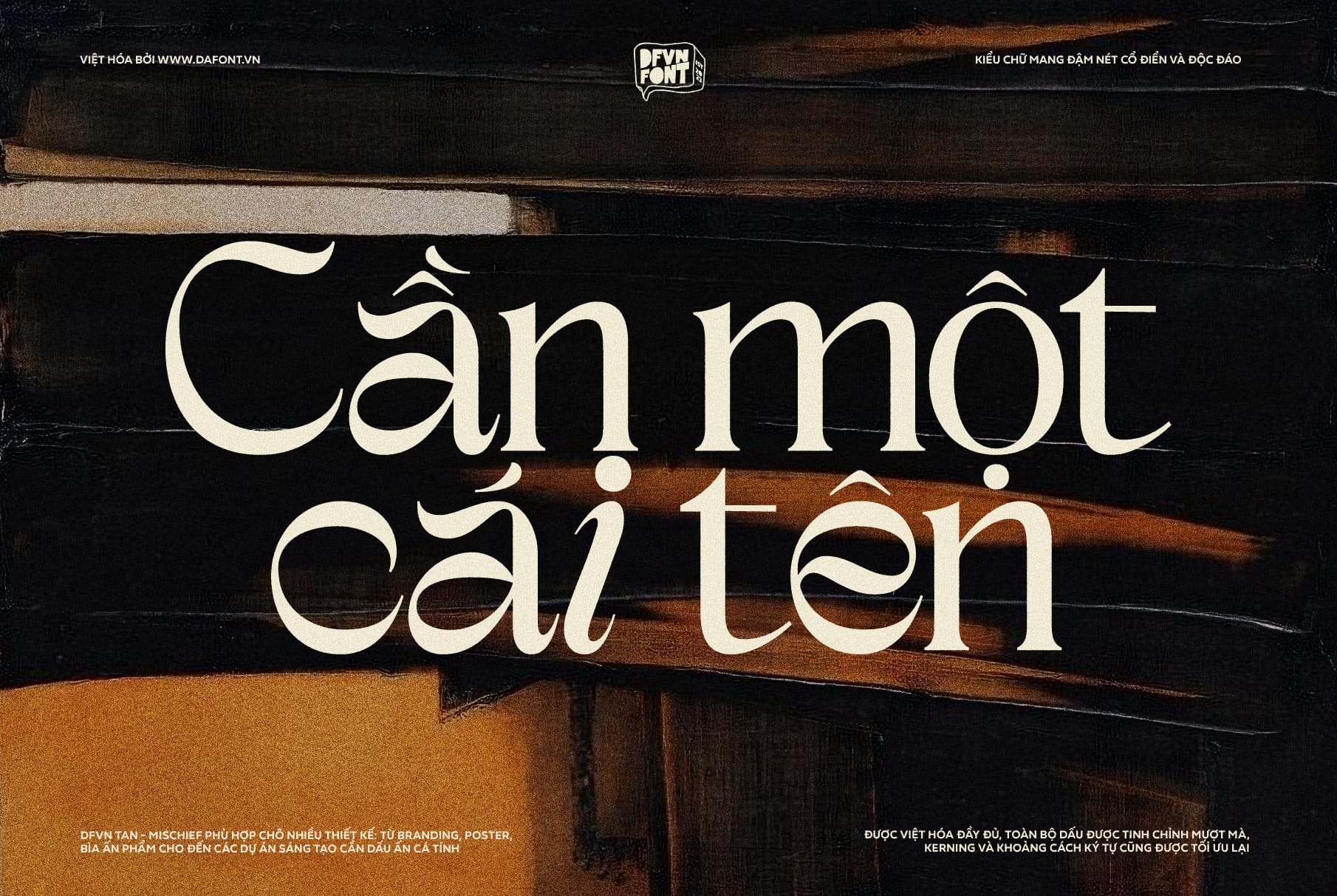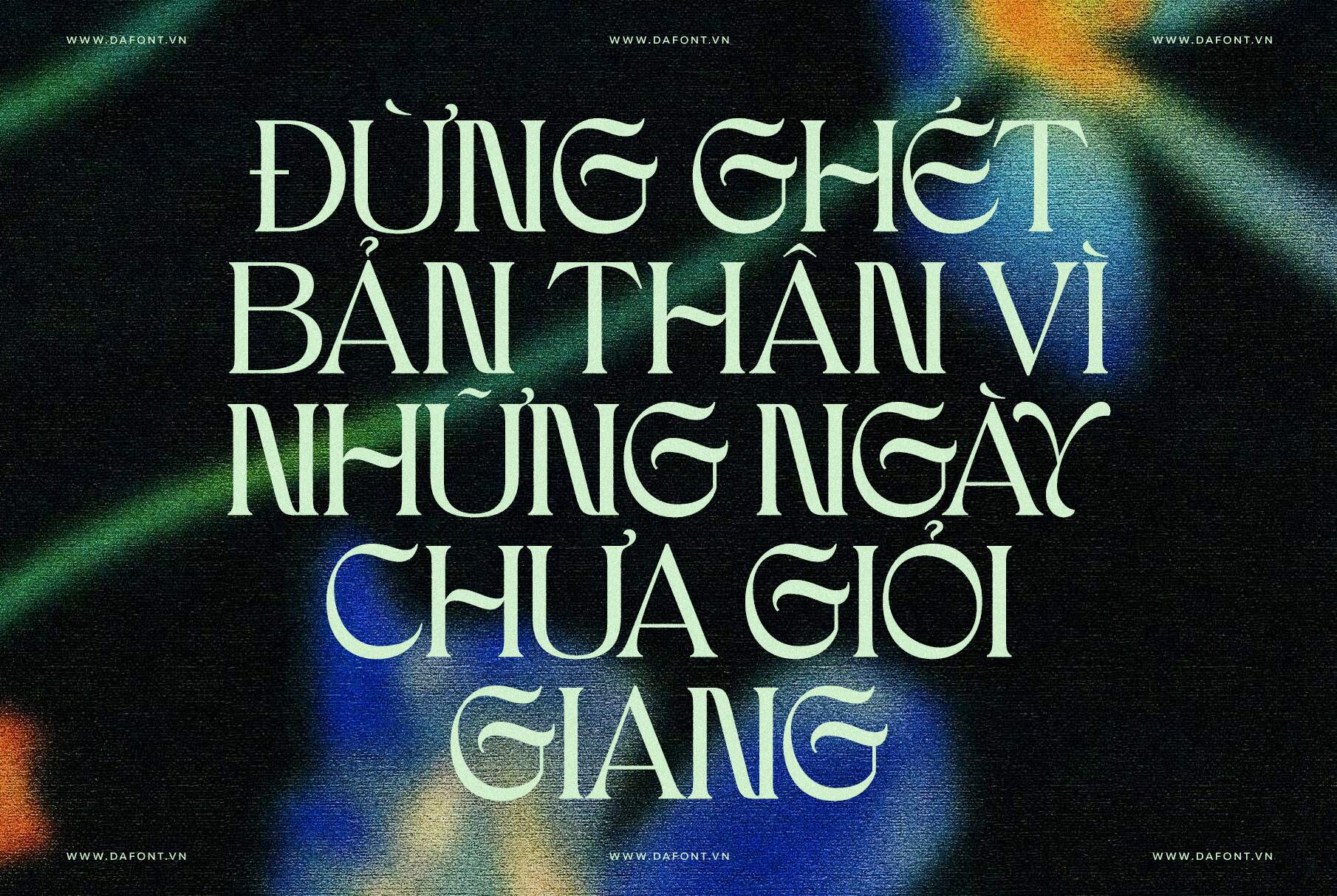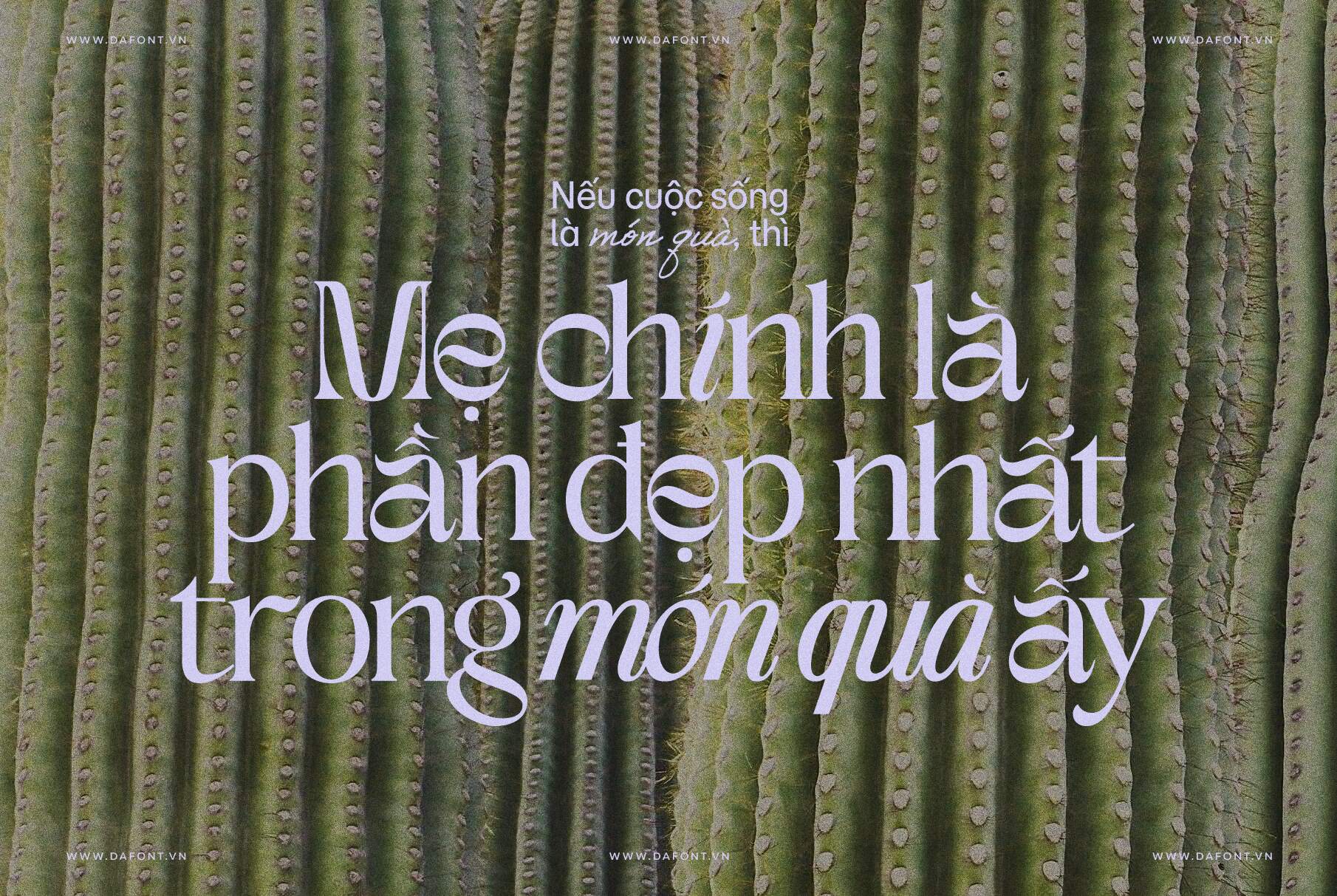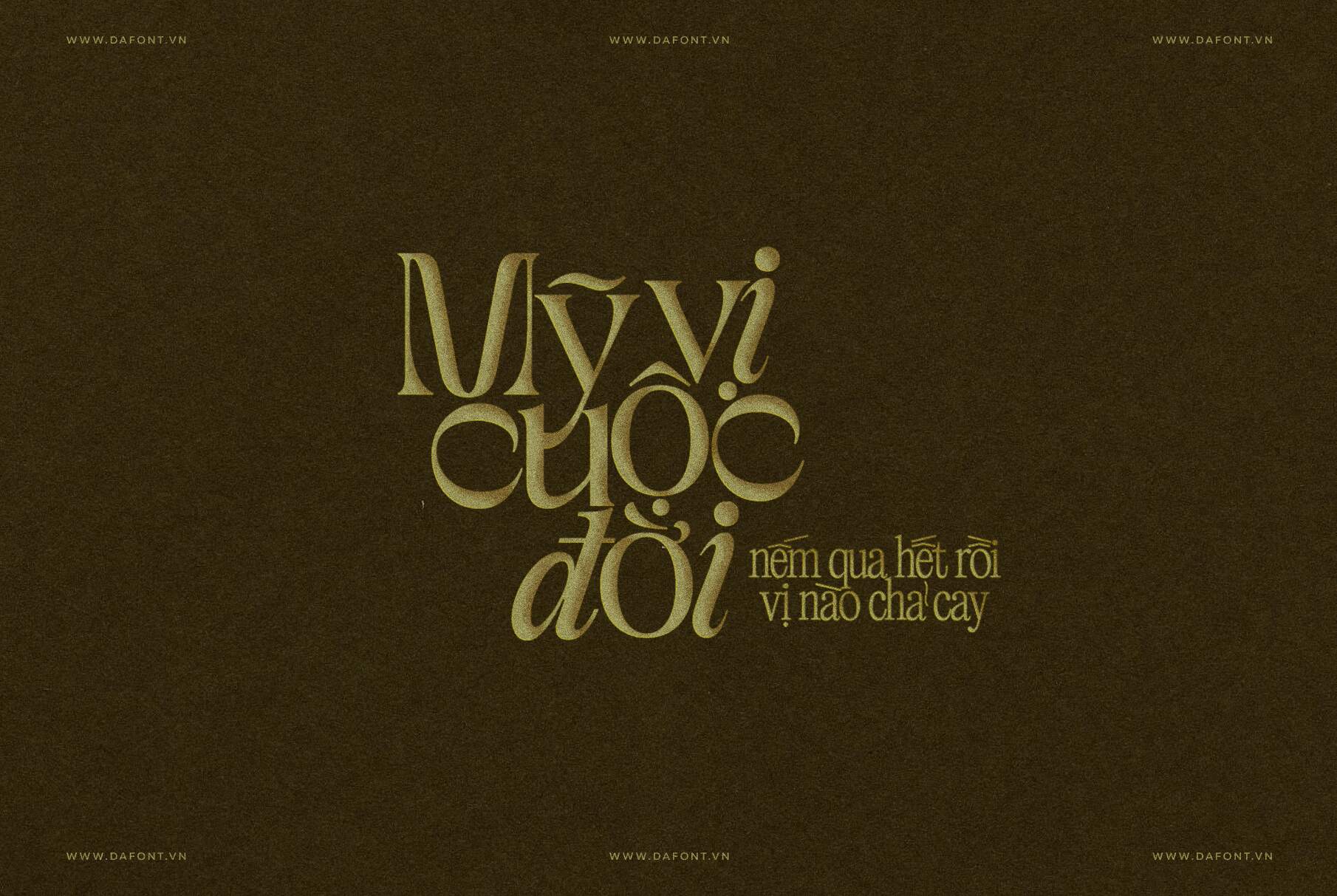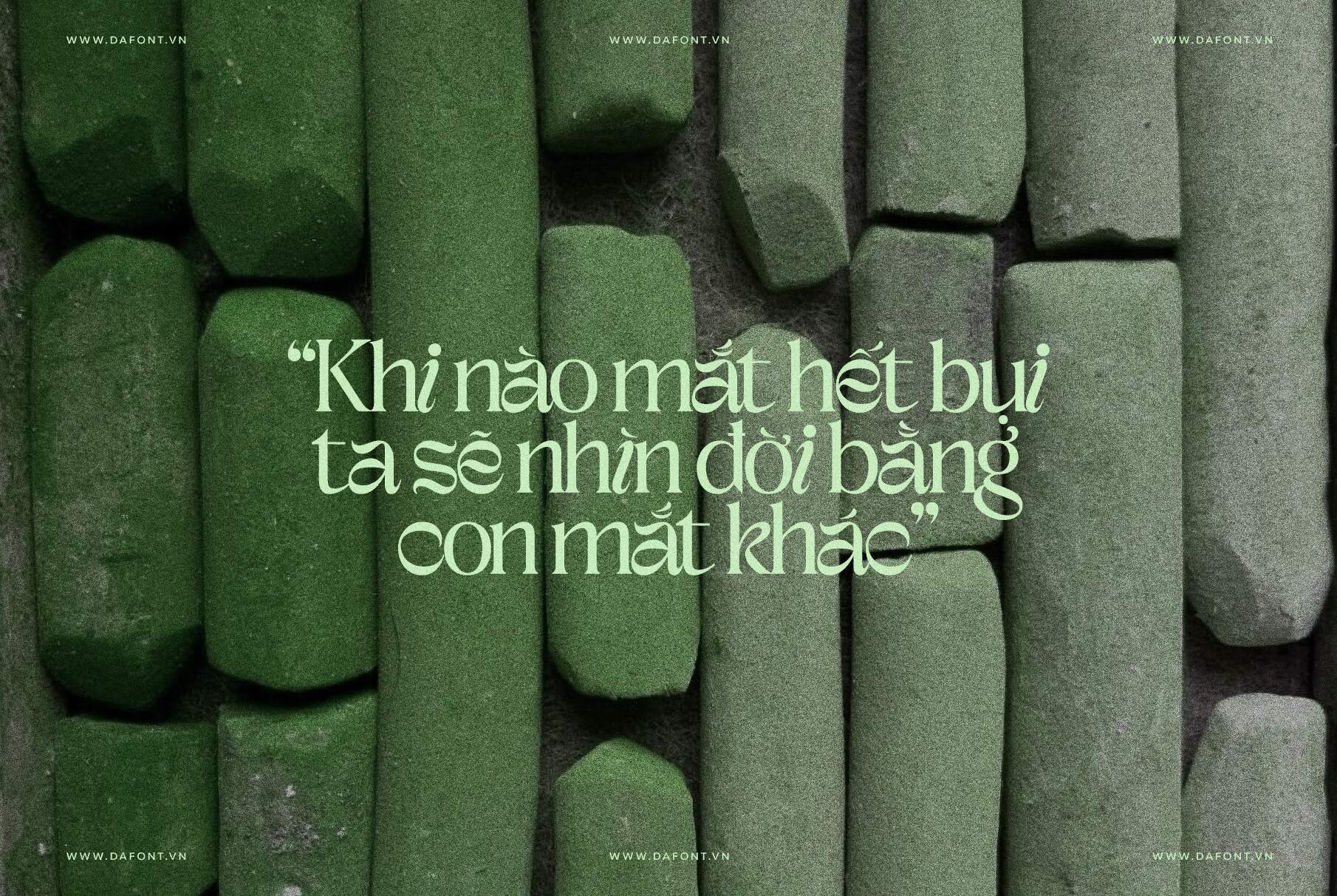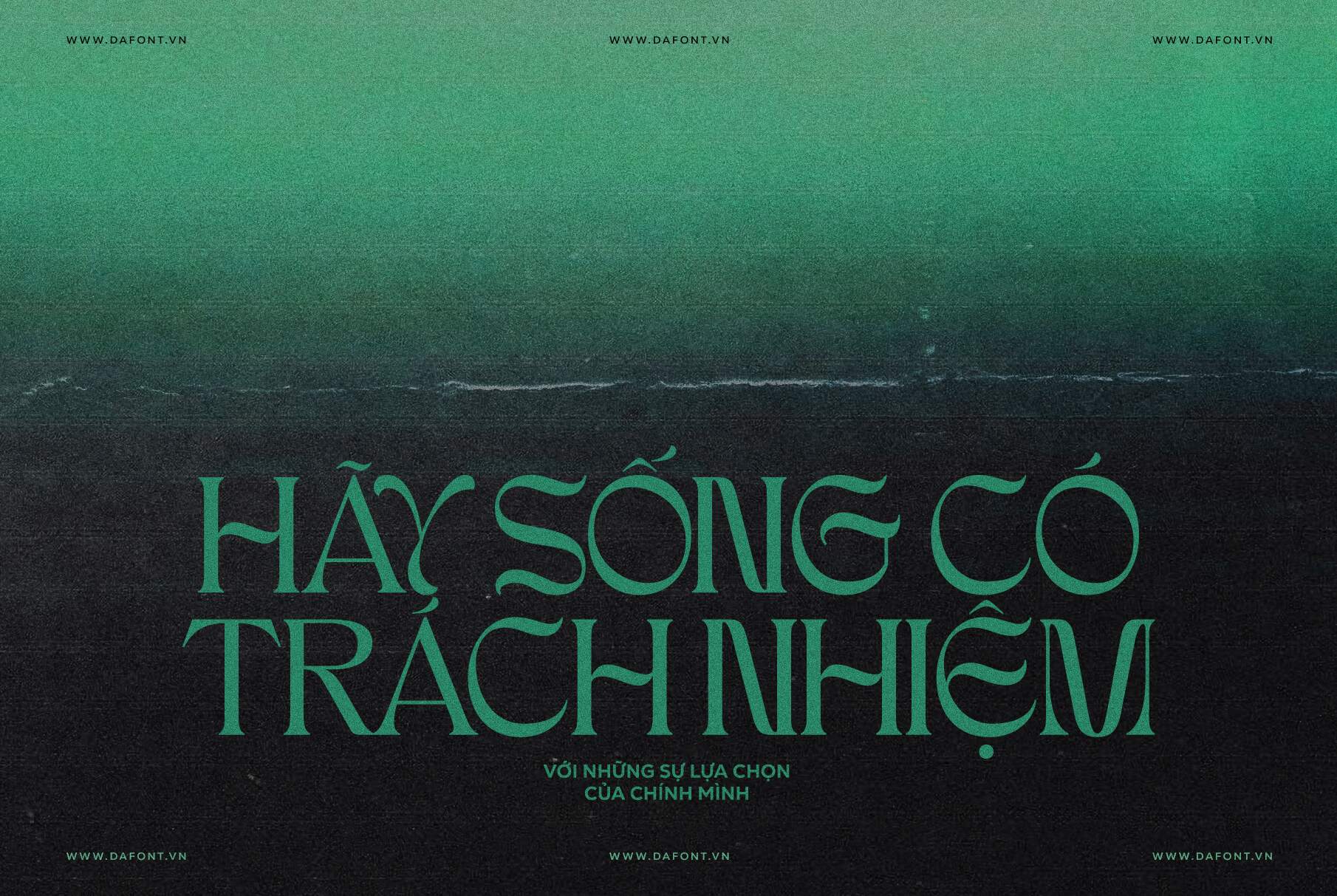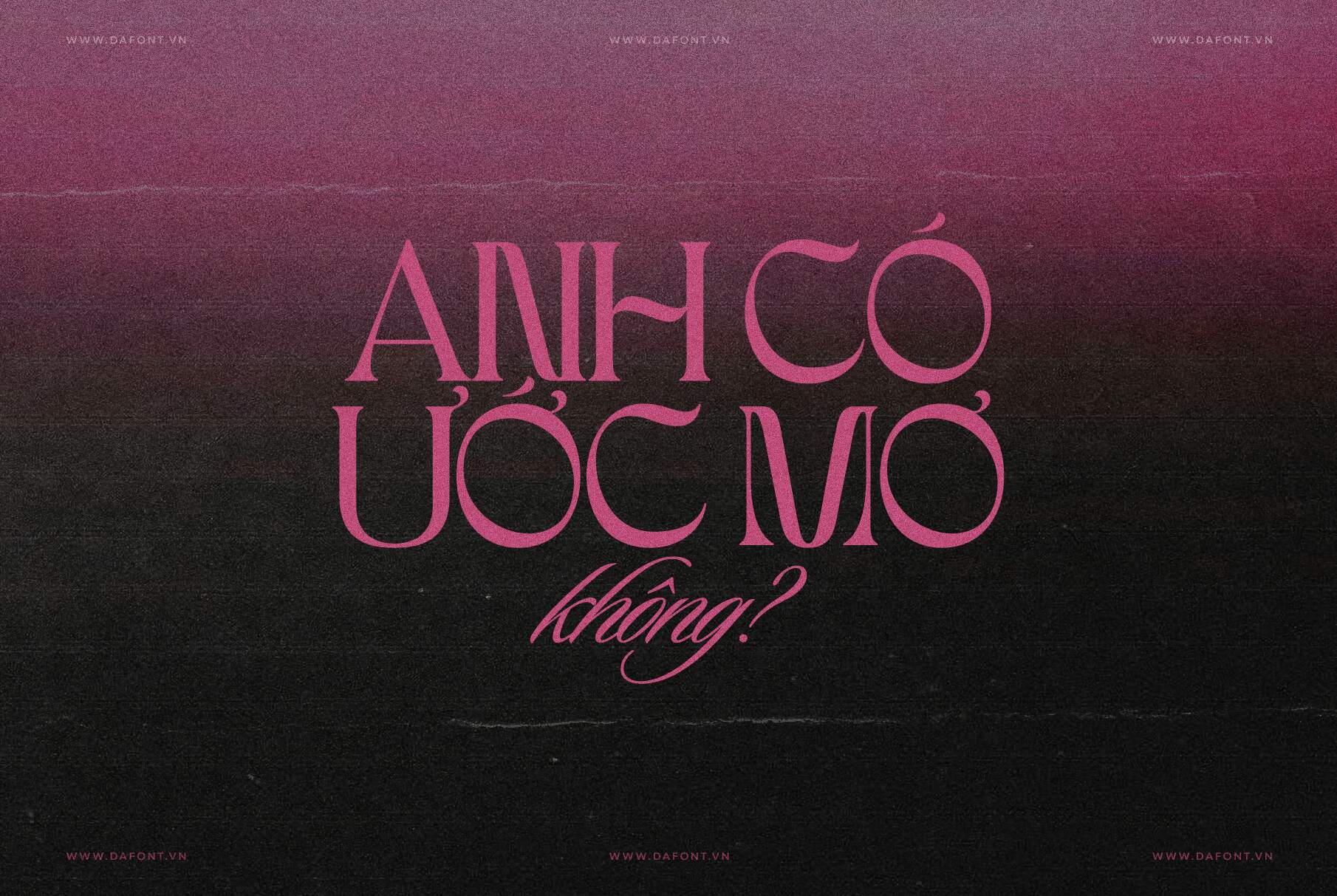
DFVN TAN – MISCHIEF là một font chữ serif hiện đại với phong cách cổ điển kết hợp yếu tố vui tươi, nghịch ngợm. Nếu bạn đang tìm kiếm một font chữ đẹp cho dự án branding, poster hay logo, TAN – MISCHIEF chắc chắn đáng để thử.
Font TAN – MISCHIEF lấy cảm hứng từ những hình dạng chữ truyền thống, nhưng không tuân theo mọi quy tắc cứng nhắc. Những đường cong bất ngờ và chi tiết thú vị tạo nên cảm giác tươi mới và thú vị cho mỗi ký tự, giúp font không chỉ phù hợp với tiêu đề lớn mà còn thể hiện tốt trong các thiết kế thương hiệu.
Điểm nổi bật của DFVN TAN - MISCHIEF
TAN - MISCHIEF là một typeface serif mang phong cách cổ điển nhưng có nét tinh nghịch, phá cách, tạo nên sự cân bằng hoàn hảo giữa tính lịch lãm và cảm giác “vui mắt” trong thiết kế.
• Hình dạng chữ cổ điển với twist hiện đại: Font lấy cảm hứng từ các hình dạng chữ serif truyền thống, nhưng được “biến tấu” bằng những đường cong bất ngờ và chi tiết độc đáo, khiến chữ vừa quen thuộc vừa thú vị. Điều này giúp font không quá nghiêm túc mà vẫn giữ được sự tinh tế.
• Phong cách vừa trang trọng vừa vui nhộn: Mischief là kiểu chữ “classic nhưng không tuân theo tất cả các quy tắc”, mang đến một cái nhìn vừa polished (trang trọng) vừa playful (vui tươi). Đây là lý do font phù hợp cho các thiết kế cần cân bằng giữa phong cách và tính sáng tạo.
• Thân thiện với nhiều dự án thiết kế: Font phù hợp dùng cho logo, in ấn, merchandise, website và social media, giúp tạo ra điểm nhấn đặc biệt trong các tiêu đề hay phần chữ lớn.
Ứng dụng phong phú
DFVN TAN - MISCHIEF font đặc biệt phù hợp với:
• Branding & Identity: Dành cho những thương hiệu cần nét chữ vừa cổ điển, vừa có điểm nhấn riêng.
• Poster & Headline: Khi bạn cần tiêu đề nổi bật, font này giúp tạo ấn tượng mạnh mẽ.
• Web & Social Media: Tiêu đề trang web, ảnh bìa, bài post mang tính nghệ thuật.
Tóm lại, TAN - MISCHIEF font là lựa chọn tuyệt vời cho các designer tìm kiếm một serif font không quá nghiêm túc nhưng vẫn đẹp, dễ đọc và giàu tính nghệ thuật.